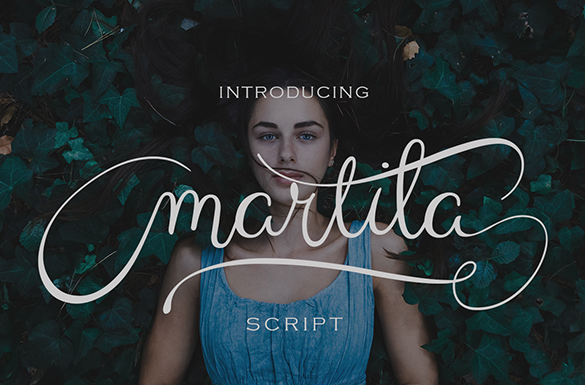
Martila Script Font – Download Grátis
A Martila Script é uma fonte script que surgiu para atender a necessidade de design personalizado e sofisticado. Inspirada no estilo do caligrafia, esta fonte moderna e clássica traz um toque suave e elegante à qualquer projeto. Ideal para aplicar em diferentes tipos de trabalhos, como convites para casamento, cartões de agradecimento, design de tinta semelhante ao água, correspondências, citações, logotipos, cabeçalhos de blog, panfletos, bandeirolas, moda e roupas, lembretes e material de papelaria. Além disso, a Martila Script suporta múltiplas línguas internacionais, tornando-a perfeita para designers que trabalham com um amplo espectro de projetos multilingues. Engajante e versátil, esta fonte é uma escolha excelente para qualquer designer em busca de uma fonte script única e sofisticada. Esta fonte foi criada por 178-MC, conhecido pela qualidade e diversidade de suas criações gráficas. A Martila Script traz à tona a delicadeza do caligrafia, transformando-a em um estilo que se adapta perfeitamente às demandas modernas de design. Com uma linguagem fluida e elegante, ela é ideal para aplicar em qualquer projeto que exija um toque único e sofisticado.